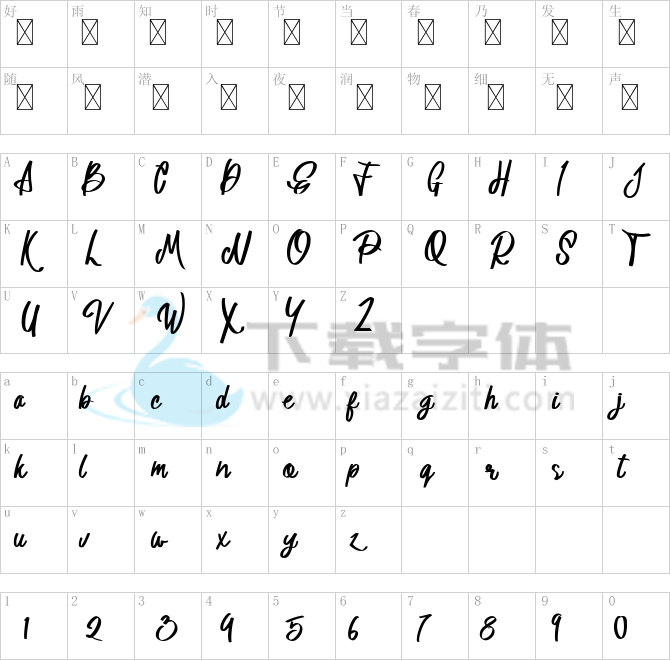
Astania.ttf字体下载
Astania.ttf字体下载,这款字体结构工整、笔画清晰,兼顾美观与易读性,适用于标题、正文、海报、包装、LOGO 等多种场景。字形优雅稳定,风格百搭耐看,适配日常排版与创意设计,让文字呈现更舒适、更具质感。Astania.ttf字体下载一笔一画,皆是细节,以均衡的比例、流畅的线条打造舒适视觉体验,字形端正大气,风格简约现代。无论是商业设计、品牌宣传还是日常排版,都能轻松驾驭,让文字更有格调与力量。Astania.ttf字体下载字体下载。